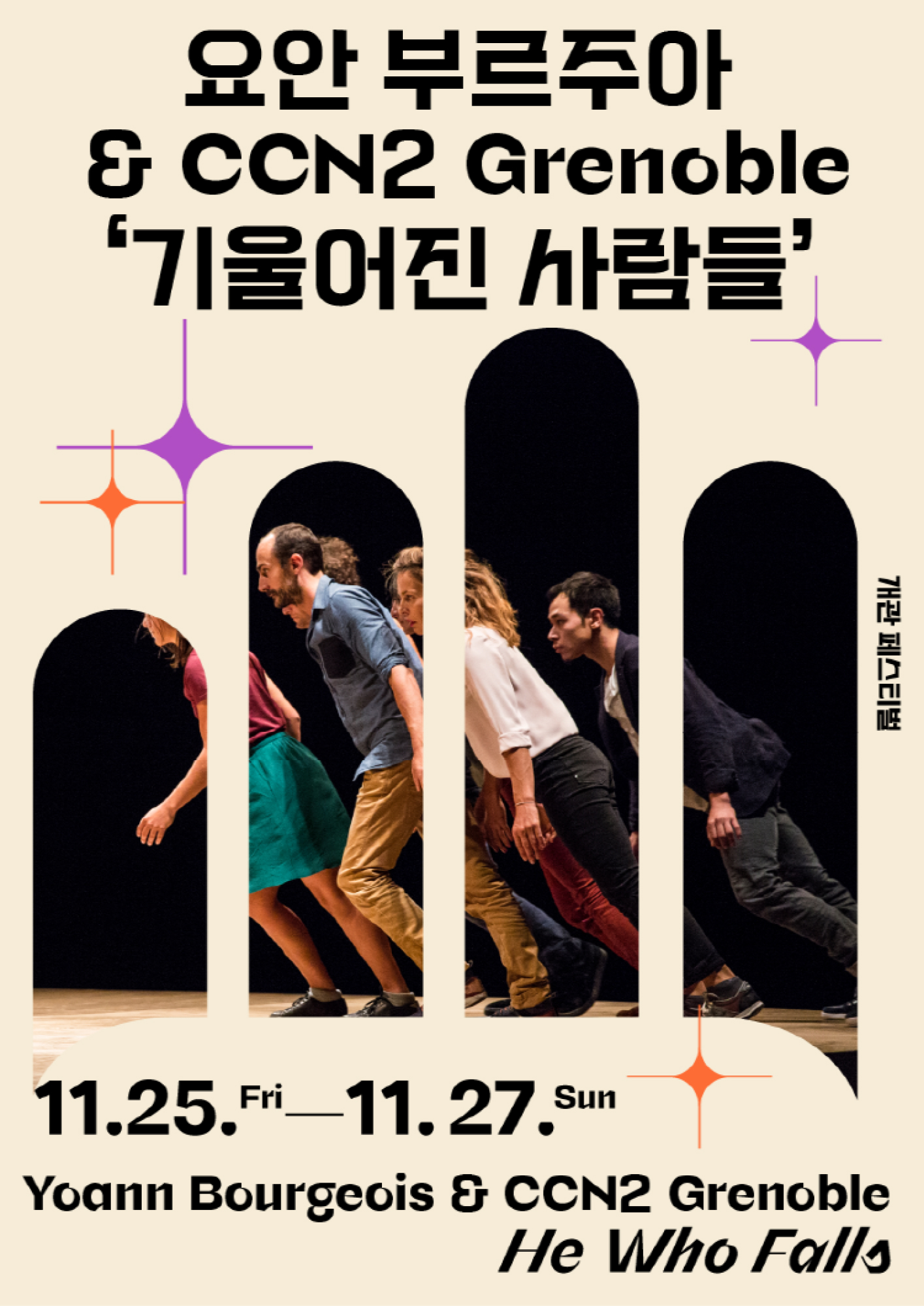
오흐탕크 Package M
Ortank Package M
“Ortank(이하 ‘오흐탕크’)”는 지오매트릭 그로테스크 계열의 서체로 기하학적 형태의 한계를 탐구한 결과물입니다. 직선형 그로테스크 스타일에서 오는 약간의 고전적인 느낌에 단순함이 결합되었습니다. 서체는 큰 단락 형식뿐만 아니라 작은 텍스트까지 여러 종류의 콘텐츠에서 사용이 가능합니다. 독특한 모양(예: 'n' 및 'u')은 불편함 없이 작은 크기에서도 가독성을 유지합니다. 디지털 느낌의 파격적인 디자인을 지닌 오흐탕크 디스플레이는 굵기가 커질수록 디자인 의도가 더 선명하게 드러납니다. 디스플레이만의 독특한 모양들을 체험해 보실 수 있습니다. (예: ‘O’, ‘A’) 또한 이탤릭체는 강하게 기울여서 역동적이면서 강력한 표현력을 지니게 제작했습니다. 단순히 수직 버전을 기울이지 않고, 보다 저희만의 독립적인 접근 방식을 취했습니다. 서로 다른 매력을 지닌 오흐탕크 텍스트(Text), (Display), (Text, Display Italic)을 만나보세요!